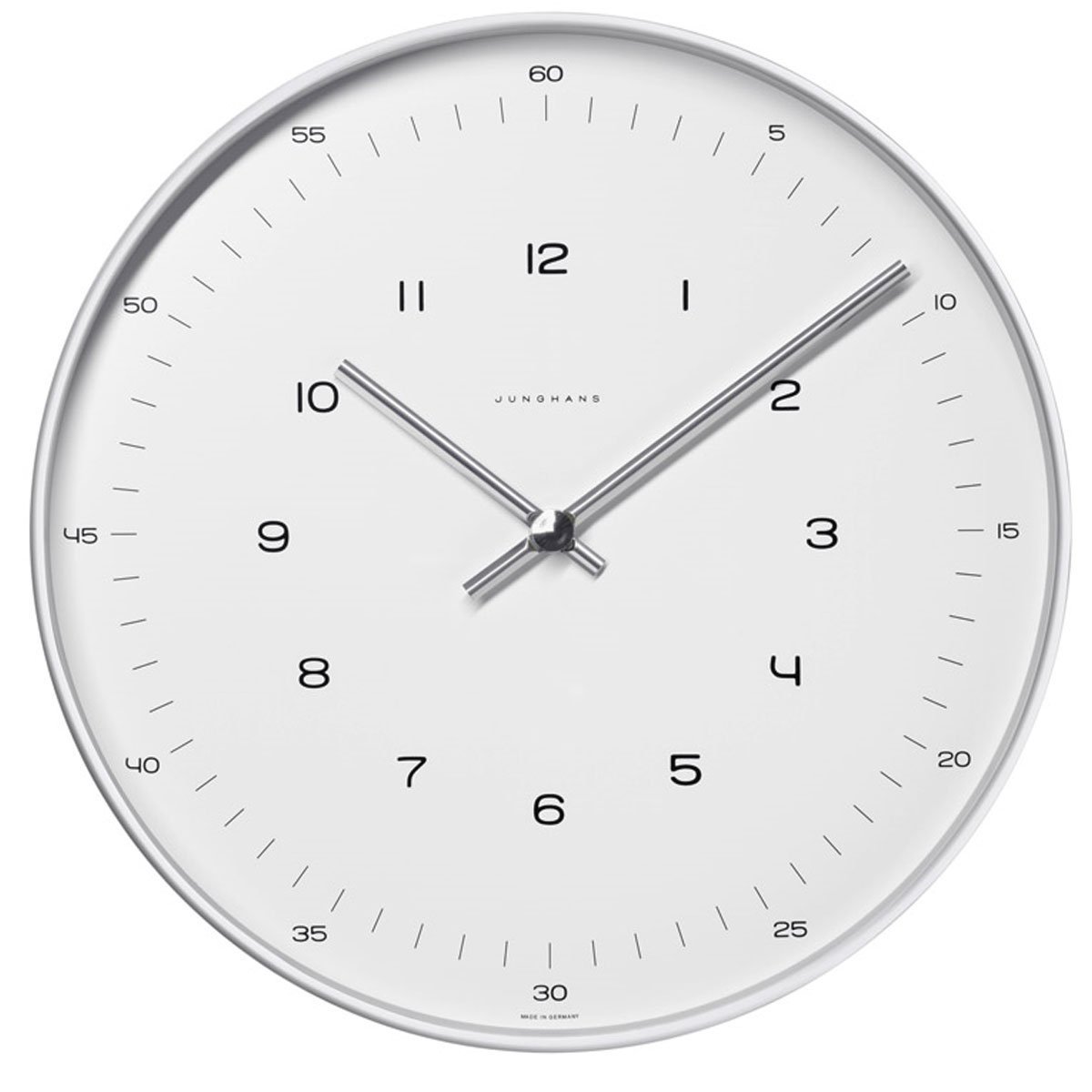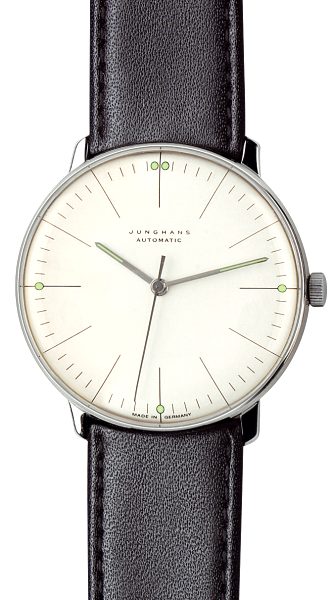
Schrift Ziffernblatt Max Bill für Junghans
Das Design ist aus den 1950er Jahren und esist sicher keine Satzschrift. Aber eventuell wurde die Schrift später digitalisiert und jemand von euch weiß wie diese Nachbau heißt oder kennt eine ähnliche Schrift ...
Ursprünglich hat der gute Herr Bill getreu der der Funktion folgenden Form aber gar keine Zahlen, sondern verschieden lange Striche, vorgesehen.